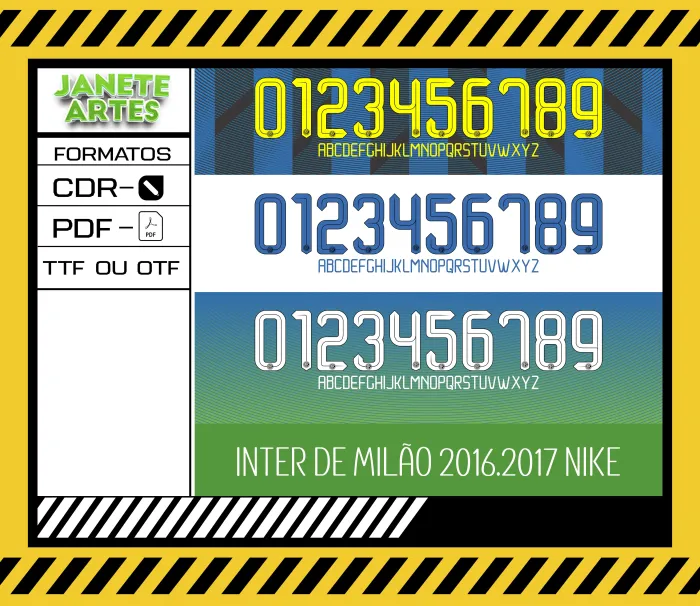
Fonte de Time Tipografia Inter de Milão 2016 - 2017
• ✅ Alfabeto completo: letras A a Z e números 0 a 9
Uma história de paixão e estilo para o seu visual
Imagina o adrenalina de uma torcida vibrando no estádio em Milão, enquanto a fonte e os números do time criam uma identidade única e marcante em cada camisa da galera. Foi assim que a Fonte de Time Tipografia Inter de Milão 2016 - 2017 conquistou fãs de futebol e design, unindo emoção e tradição em um só estilo. Se você é apaixonado pelo futebol e quer levar essa vibe para o seu look, este arquivo é para você!